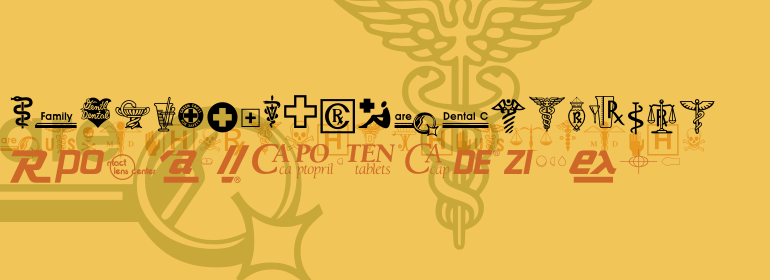
Medical & Pharmaceutical
Medical & Pharmaceutical,这款字体结构工整、笔画清晰,兼顾美观与易读性,适用于标题、正文、海报、包装、LOGO 等多种场景。字形优雅稳定,风格百搭耐看,适配日常排版与创意设计,让文字呈现更舒适、更具质感。Medical & Pharmaceutical一笔一画,皆是细节,以均衡的比例、流畅的线条打造舒适视觉体验,字形端正大气,风格简约现代。无论是商业设计、品牌宣传还是日常排版,都能轻松驾驭,让文字更有格调与力量。Medical & Pharmaceutical字体下载。